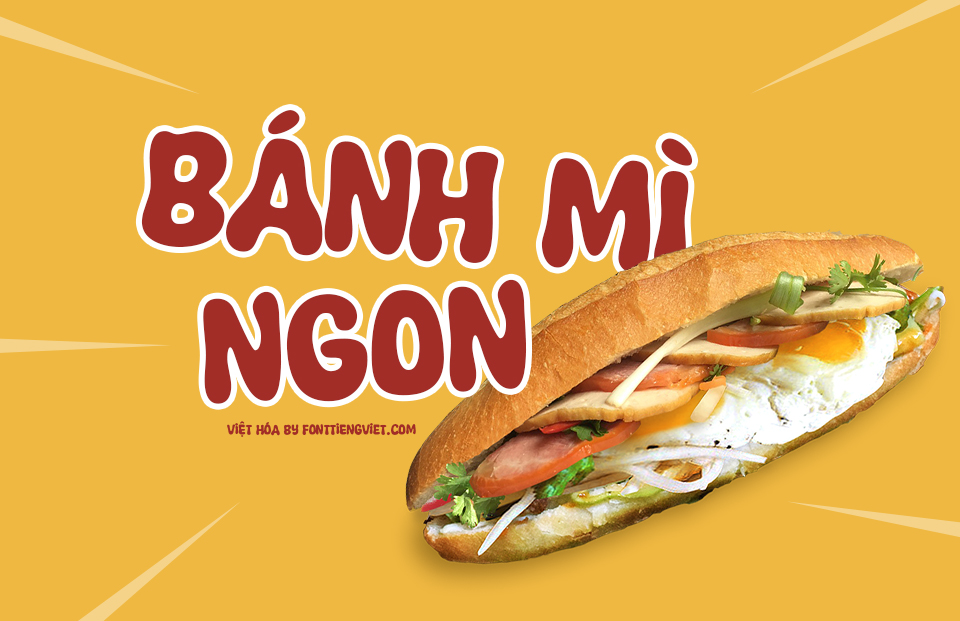
Font Việt hóa 1FTV VIP Super Funtime
Giới thiệu về bộ Font Việt hóa 1FTV VIP Super Funtime
Chào mừng các bạn đến với thế giới sáng tạo đầy màu sắc dành riêng cho học đường. Trong cộng đồng thiết kế, việc tìm kiếm một bộ font vừa mang tính giải trí vừa chuyên nghiệp là điều không hề dễ dàng. Bộ Font Việt hóa 1FTV VIP Super Funtime chính là giải pháp hoàn hảo giúp các bạn học sinh và giáo viên tạo nên những ấn phẩm độc đáo. Khi nhắc đến Font Miễn Phí, chúng ta thường nghĩ đến những định dạng cơ bản, nhưng 1FTV VIP Super Funtime lại mang một phong cách vui nhộn, phóng khoáng và tràn đầy năng lượng tích cực cho mọi dự án đồ họa.
Đặc điểm nổi bật của Font Việt hóa 1FTV VIP Super Funtime
Bộ font này nổi bật với những đường nét bo tròn, đầy đặn, tạo cảm giác thân thiện và gần gũi. Điểm cộng lớn nhất là khả năng hiển thị tiếng Việt trọn vẹn, không bị lỗi dấu, giúp việc soạn thảo văn bản trở nên trơn tru. Bạn có thể sử dụng bộ font này để làm tiêu đề bài báo tường, thiết kế thiệp mời hay trang trí các slide thuyết trình sinh động. Sự linh hoạt trong đường nét giúp 1FTV VIP Super Funtime dễ dàng chinh phục người xem ngay từ cái nhìn đầu tiên.
Cách ứng dụng Font Việt hóa 1FTV VIP Super Funtime hiệu quả
Để tối ưu hóa vẻ đẹp của font chữ này, các bạn nên kết hợp với những tông màu tươi sáng như vàng, xanh lá hoặc cam. Trong môi trường giáo dục, việc sử dụng font chữ phù hợp sẽ giúp học sinh hào hứng hơn với bài học. Bạn có thể áp dụng 1FTV VIP Super Funtime cho:
• Thiết kế bìa sách bài tập và sổ tay ghi chép.
• Làm poster thông báo các hoạt động ngoại khóa.
• Tạo hình ảnh minh họa cho các video clip học tập.
Kết luận về bộ font chữ ấn tượng